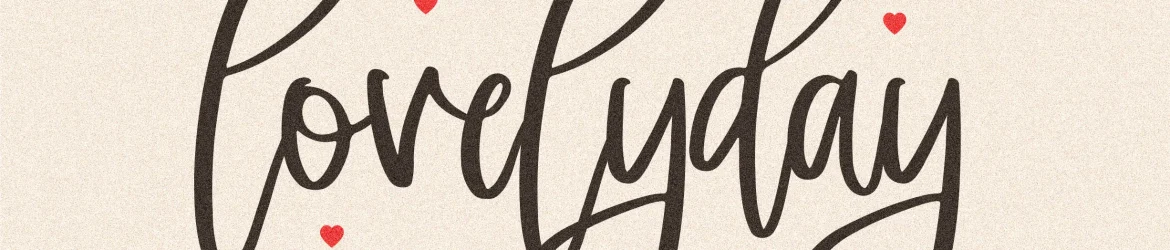
Lovelyday Font – Download Grátis
Esta é uma fonte escrita à mão ideal para diversos projetos, desde logotipos e design de marca até etiquetas, cartões de convite e capas de livros. Seu toque suave e natural cria um ar de exclusividade que combina perfeitamente com produtos como copos personalizados, malaadesigns, carteiras e até mesmo a sua própria identidade visual. Ideal para expressar sentimentos pessoais em cartões de aniversário ou mensagens memoráveis, este é também perfeito para um toque único e delicado no seu trabalho fotográfico. As suas linhas flexíveis são ideias para criar um charme especial que torna qualquer projeto sua criação única. Essa fonte escrita à mão é perfeita para adicionar um toque pessoal a qualquer peça, seja uma etiqueta de latinha ou o design da sua própria marca. Que tal dar aos seus clientes algo autêntico e bem pensado com o charme único deste design?